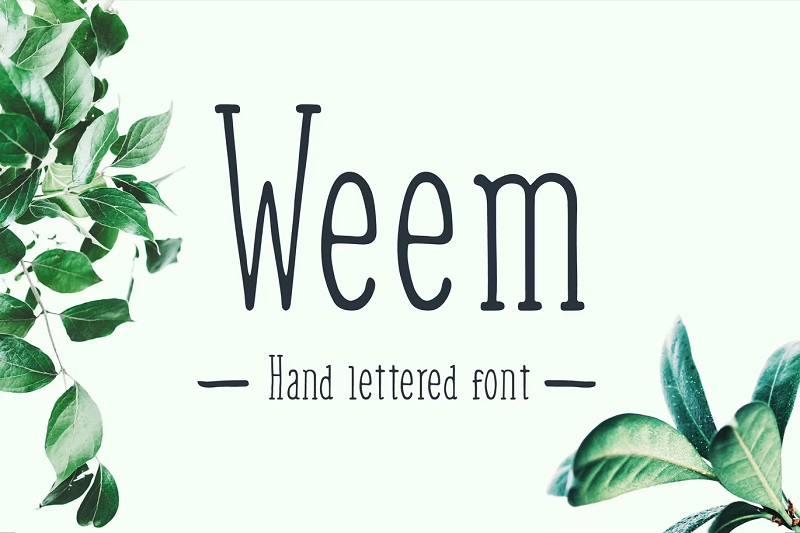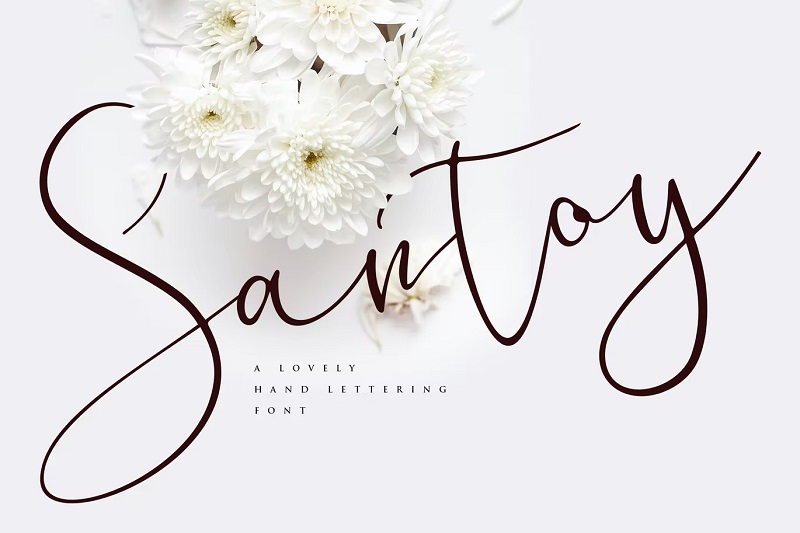
28 Font Huruf Tangan Terbaik (Gratis & Premium) – 2022
Diterbitkan: 2022-04-25Ingin font yang unik dan berkarakter untuk melengkapi desain Anda? Anda membutuhkan font tulisan tangan.
Font tulisan tangan atau font yang digambar tangan sangat cocok untuk menambahkan beberapa gaya dan bakat kreatif pada desain artistik. Namun, internet dipenuhi dengan ribuan font yang digambar tangan, dan mungkin sulit untuk memilih yang tepat untuk desain Anda.
Itulah mengapa kami mengumpulkan daftar font tulisan tangan terbaik yang tersedia secara online. Kami telah menyertakan 28 font yang sesuai dengan setiap gaya, serta campuran opsi gratis dan premium.
Sebelum kita masuk ke daftar, mari kita lihat apa itu font tulisan tangan dan bagaimana cara menggunakannya.
Apa itu Font Huruf Tangan?
Font tulisan tangan adalah font yang telah digambar dengan tangan alih-alih menggunakan program digital untuk membuat karakter. Karena digambar dengan tangan, setiap huruf menjadi unik dan ini dapat membantu memberi desain Anda lebih banyak bakat dan karakter.
Dengan font yang telah dirancang secara digital, semuanya sedikit lebih seragam, dan Anda tidak akan melihat tepi kasar atau bakat unik seperti yang Anda lakukan dengan font tulisan tangan.
Font tulisan tangan populer di kalangan desainer dan sering digunakan untuk membuat desain artistik seperti logo, kutipan, dan poster.
28 Font Huruf Tangan Gratis dan Premium Terbaik
Sekarang kita telah belajar sedikit lebih banyak tentang apa itu font tulisan tangan, mari masuk ke daftar, dimulai dengan favorit kita…
1. Devilion – Pilihan Utama Kami
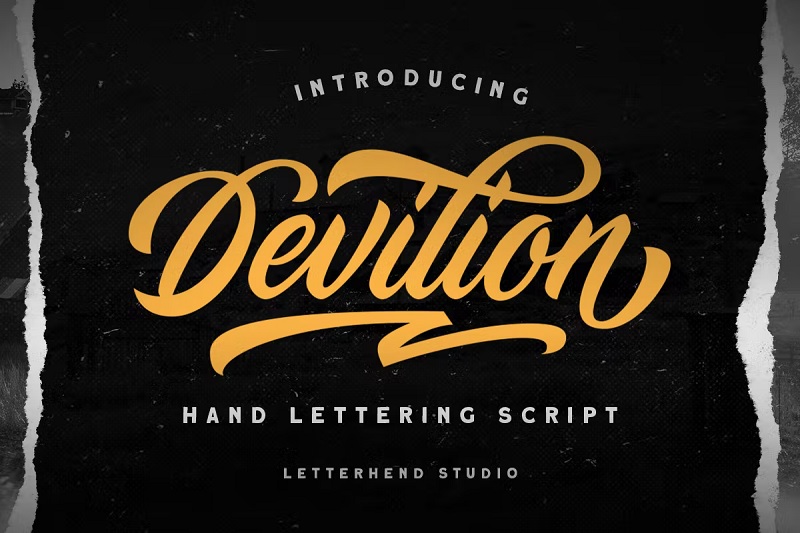
Devilion adalah font tulisan tangan yang halus dan montok (dan font paling populer dalam kategori ini di Envato Elements). Ini super stylish dan dapat digunakan dalam berbagai desain yang berbeda. Meskipun Devilion ditulis dalam gaya kursif, itu masih sangat jelas dan mudah dibaca, membuatnya sempurna untuk hampir semua proyek.
Mengapa ini pilihan utama kami?
Kami menyukai font ini karena bergaya, serbaguna, dan sangat mudah dibaca. Baik Anda menggunakannya sebagai bagian dari logo, atau pada t-shirt atau merchandise, font ini akan membantu desain Anda terlihat profesional dan unik.
2. Font Huruf Tangan Backabon
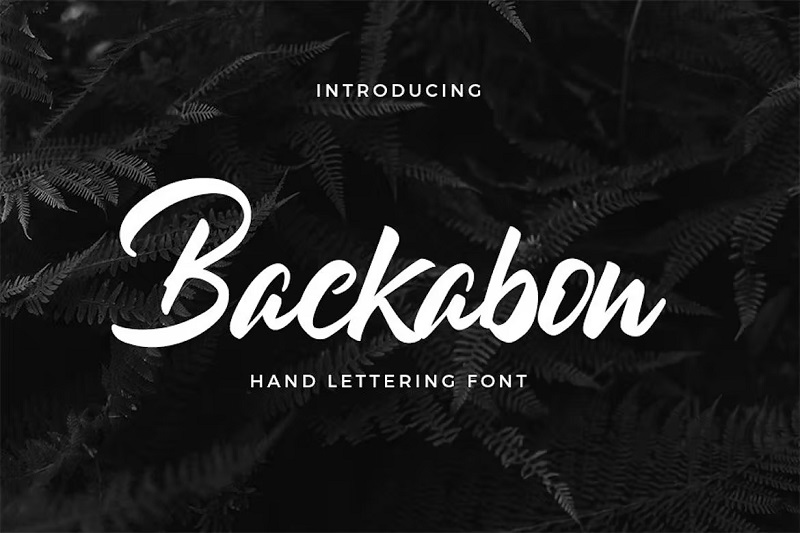
Backabon adalah font tulisan tangan bergaya kursif. Font tebal ini sangat berkelas dan akan terlihat bagus di alat tulis, kartu nama, poster, dan banyak lagi. Backabon cukup terbaca tetapi akan terlihat paling baik digunakan dalam teks header daripada di badan teks yang lebih kecil.
3. Daytonia
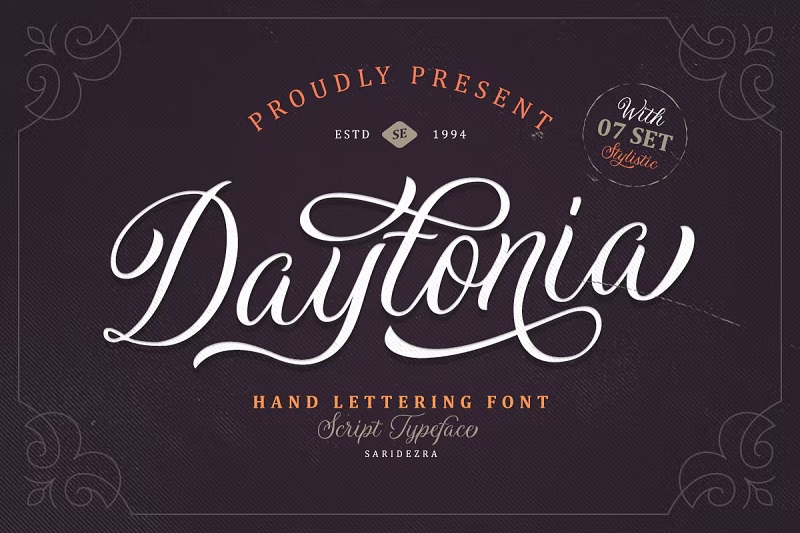
Daytonia adalah font tulisan tangan elegan lainnya yang akan bekerja dengan baik di berbagai jenis desain. Ekor dan swash yang panjang dan melingkar menambah karakter dan sentuhan elegan yang akan membuatnya sangat cocok untuk desain elegan seperti undangan pernikahan.
4. Tahan lama
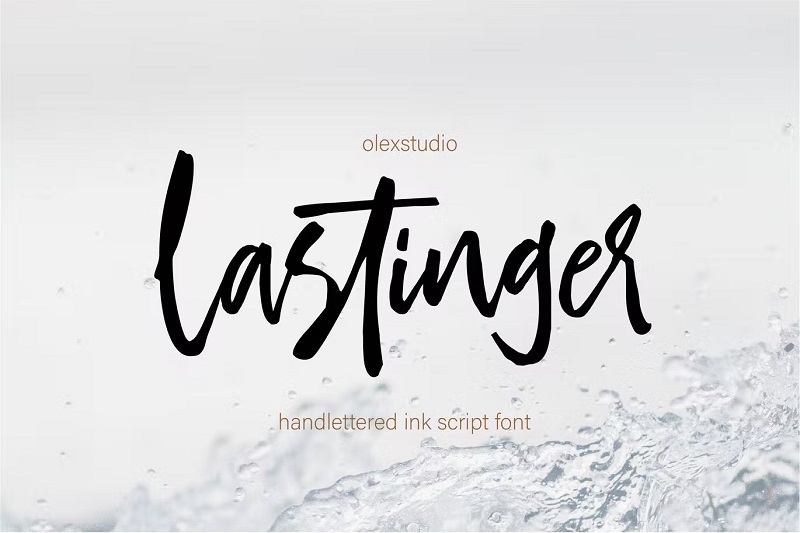
Lastinger adalah font skrip tinta tulisan tangan dari desainer Olexstudio. Meskipun tetap chic dan bergaya, bentuk huruf yang mencolok terlihat kurang halus dan lembut dibandingkan font tulisan tangan lainnya yang telah kita lihat sejauh ini, yang menjadikan font ini pilihan yang baik untuk desain 'edgier'.
5. Brilganttyne
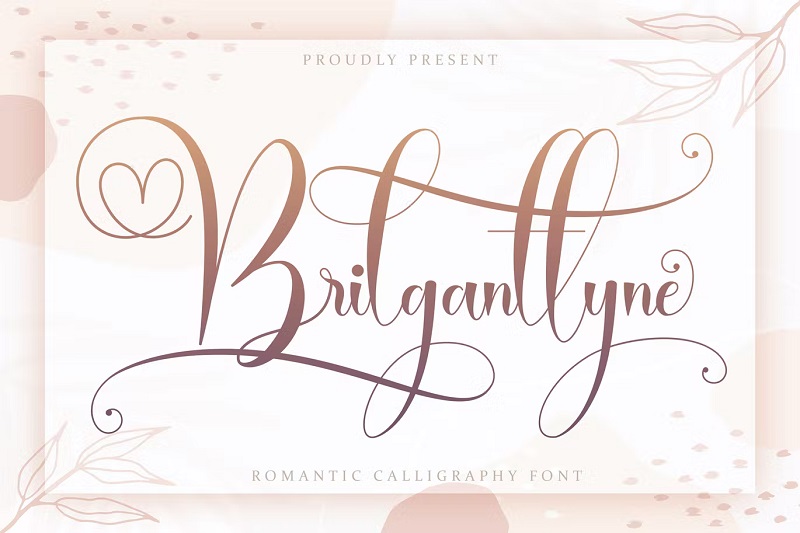
Ingin menyuntikkan sedikit cinta atau romansa ke dalam desain Anda? Ini adalah font untuk Anda. Brilganttyne adalah font kaligrafi romantis dengan pola melingkar unik yang membentuk bentuk hati. Ini adalah jenis huruf yang sempurna untuk kartu ucapan hari Valentine, undangan pernikahan, sampul buku roman, dan semua proyek bertema cinta lainnya.
6. Font Huruf Tangan Chervil
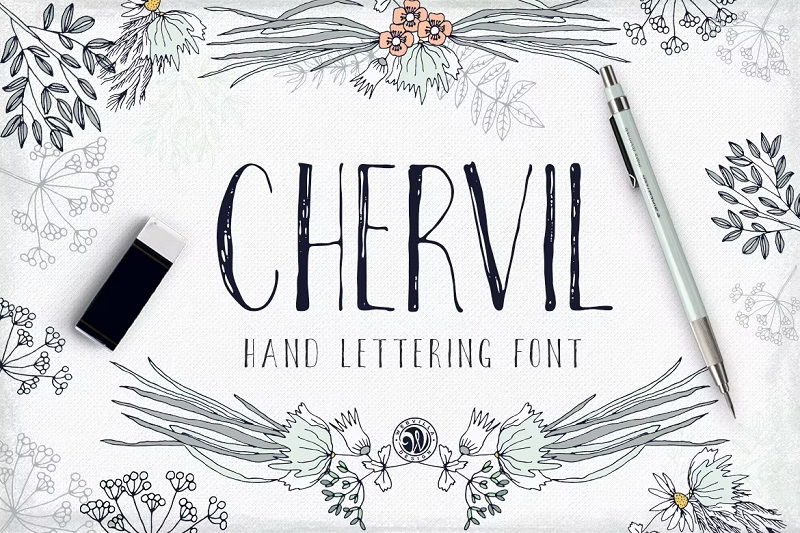
Chervil adalah font gambar tangan yang benar-benar unik dengan nuansa minimalis. Tidak seperti banyak font tulisan tangan, Chervil tidak kursif dan memiliki karakter sempit yang sangat mudah dibaca. Jika Anda ingin membuat desain unik dan modern dengan nuansa minimalis, maka font ini cocok untuk Anda.
7. Font Digambar Tangan Belgedes
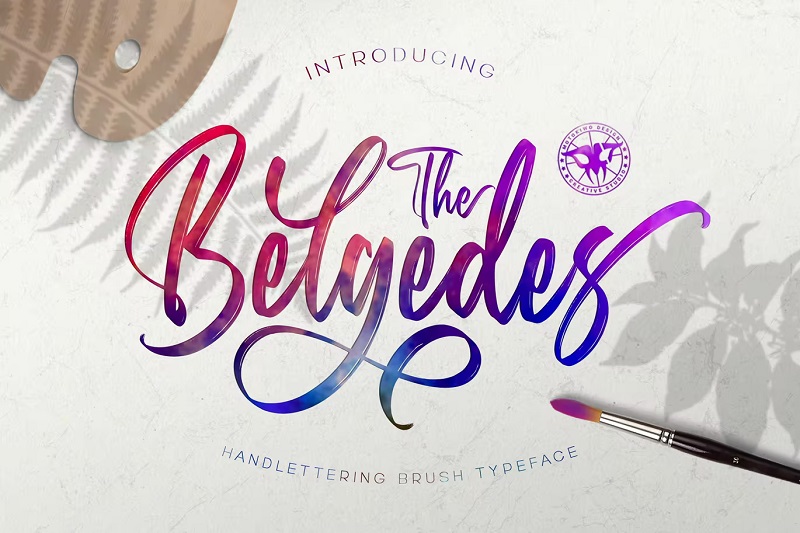
Belgedes adalah font yang digambar tangan dengan gaya skrip kuas. Font ini berpasangan sempurna dengan font serif, dan dapat digunakan untuk membuat desain yang menarik dan menarik. Paket font juga mencakup ligatur dan set lengkap karakter alternatif gaya yang memberikan banyak fleksibilitas saat membuat desain Anda.
28. Font Sketsa Bolgen
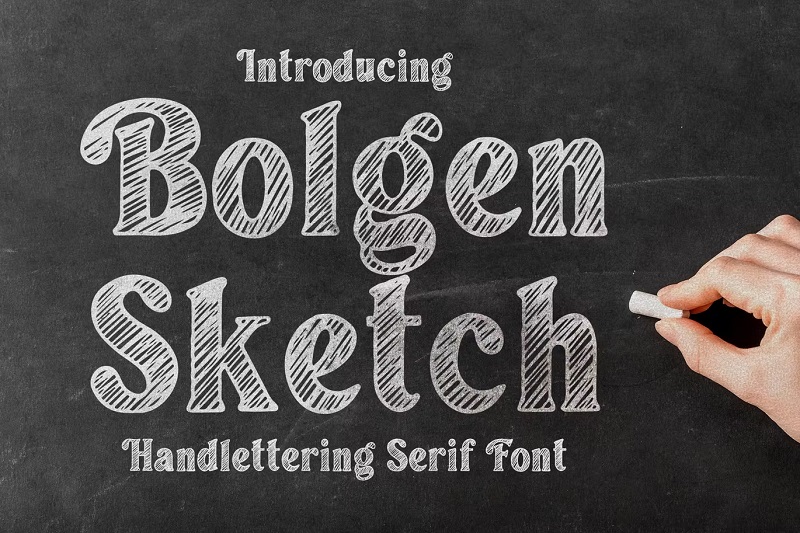
Bolgen adalah font yang digambar tangan dengan efek papan tulis yang sempurna untuk digunakan di restoran, kafe, dan bahkan di lingkungan sekolah. Karakter yang berani akan dengan mudah menarik perhatian orang yang lewat dan membuat desain Anda lebih menarik dan menarik secara visual. Paket font Bolgen mencakup karakter huruf besar dan kecil serta angka dan tanda baca.